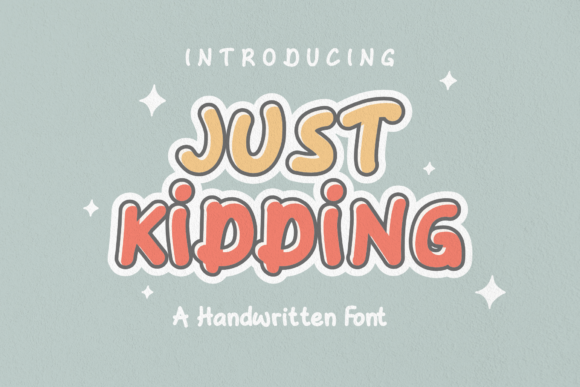
Just Kidding
Just Kidding – A Fonte Manuscrita que Transforma Seu Projeto
Se você procura um toque autêntico e artesanal para quotes, logos, branding ou qualquer material de marketing, a Just Kidding é a escolha perfeita. Essa fonte hand‑written foi desenhada para trazer personalidade e fluidez, mantendo a legibilidade em títulos, capas de revistas e peças publicitárias.
- Estilo manuscrito autêntico: linhas soltas e variações de traço que simulam a escrita à mão.
- Codificação PUA (Private Use Area): permite acessar facilmente todos os glifos e alternativas, ampliando as opções de design.
- Versatilidade de uso: funciona impecavelmente em headlines, posts de redes sociais, embalagens, identidade visual e muito mais.
Por que Just Kidding se destaca no SEO de design?
Ao escolher uma fonte que combina estética e funcionalidade, você melhora a experiência do usuário e a taxa de permanência na página. O uso estratégico de Just Kidding em títulos e chamadas de ação pode:
- Aumentar a relevância visual e, consequentemente, o tempo de leitura.
- Reduzir a taxa de bounce ao criar uma identidade única e memorável.
- Facilitar a indexação de imagens e PDFs que contenham texto estilizado, pois a fonte é reconhecível pelos motores de busca.
Como aplicar Just Kidding no seu projeto
- Quotes inspiradores: combine a fonte com fundos neutros para destacar a mensagem.
- Logotipos de marcas artesanais: use as variações de glifos para criar símbolos exclusivos.
- Capa de revistas e e‑books: títulos em Just Kidding chamam atenção nas prateleiras digitais.
- Materiais de branding: cartões de visita, etiquetas e embalagens ganham um toque pessoal.
Just Kidding não é apenas mais uma fonte manuscrita – é uma ferramenta de design completa que oferece flexibilidade, estilo e otimização SEO. Seja para um projeto profissional ou para dar aquele charme pessoal ao seu conteúdo, ela entrega resultados impactantes sem esforço.